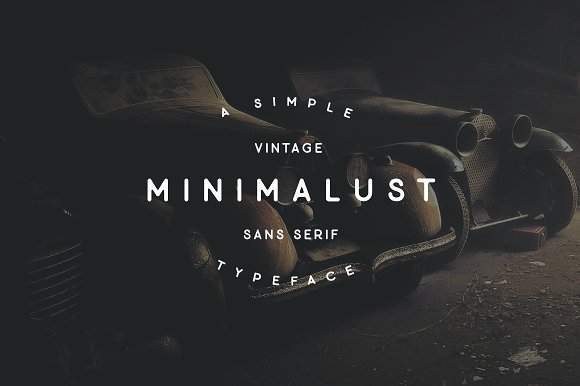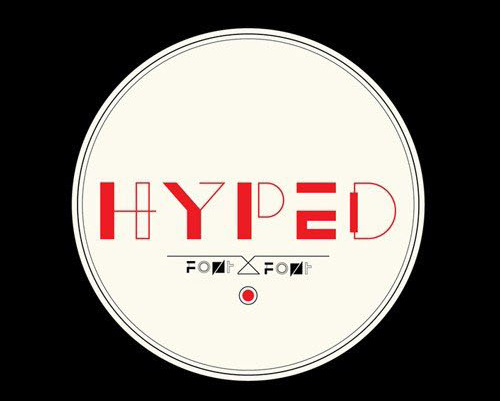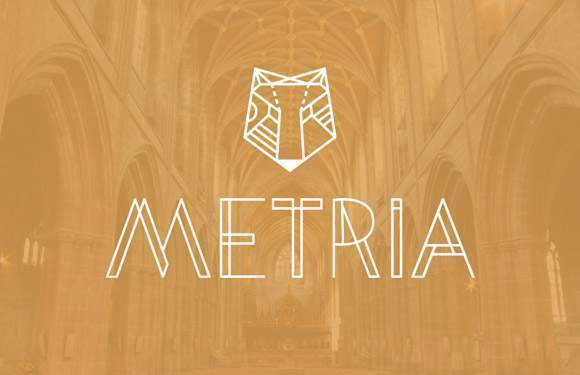
Discover an extensive collection of modern fonts curated specifically for designers who want to elevate their creative projects. Whether you’re working on branding, websites, social media graphics, posters, or print layouts, having the right fonts for designers is essential for achieving a polished and professional look.
Why Modern Fonts Matter
Using modern fonts in your design projects ensures your work feels current, stylish, and impactful. Clean, contemporary typefaces improve readability, highlight key content, and add personality to your visuals. Designers everywhere know that choosing the right free fonts can make the difference between a good design and an outstanding one.
Features of This Free Font Collection
This carefully curated selection of fonts for designers includes:
Sleek sans-serif fonts for minimalist and modern designs
Elegant serif fonts for sophisticated branding
Playful and creative handwritten fonts
Bold display fonts for eye-catching headlines
1. Lombok Font
2. Ailerons Font
Ailerons – это шрифт Adilson Gonzales de Oliveira Junior, вдохновленный моделями самолетов 1940-х годов. Концы каждой буквы наклонены и слегка изогнуты для тонких деталей.
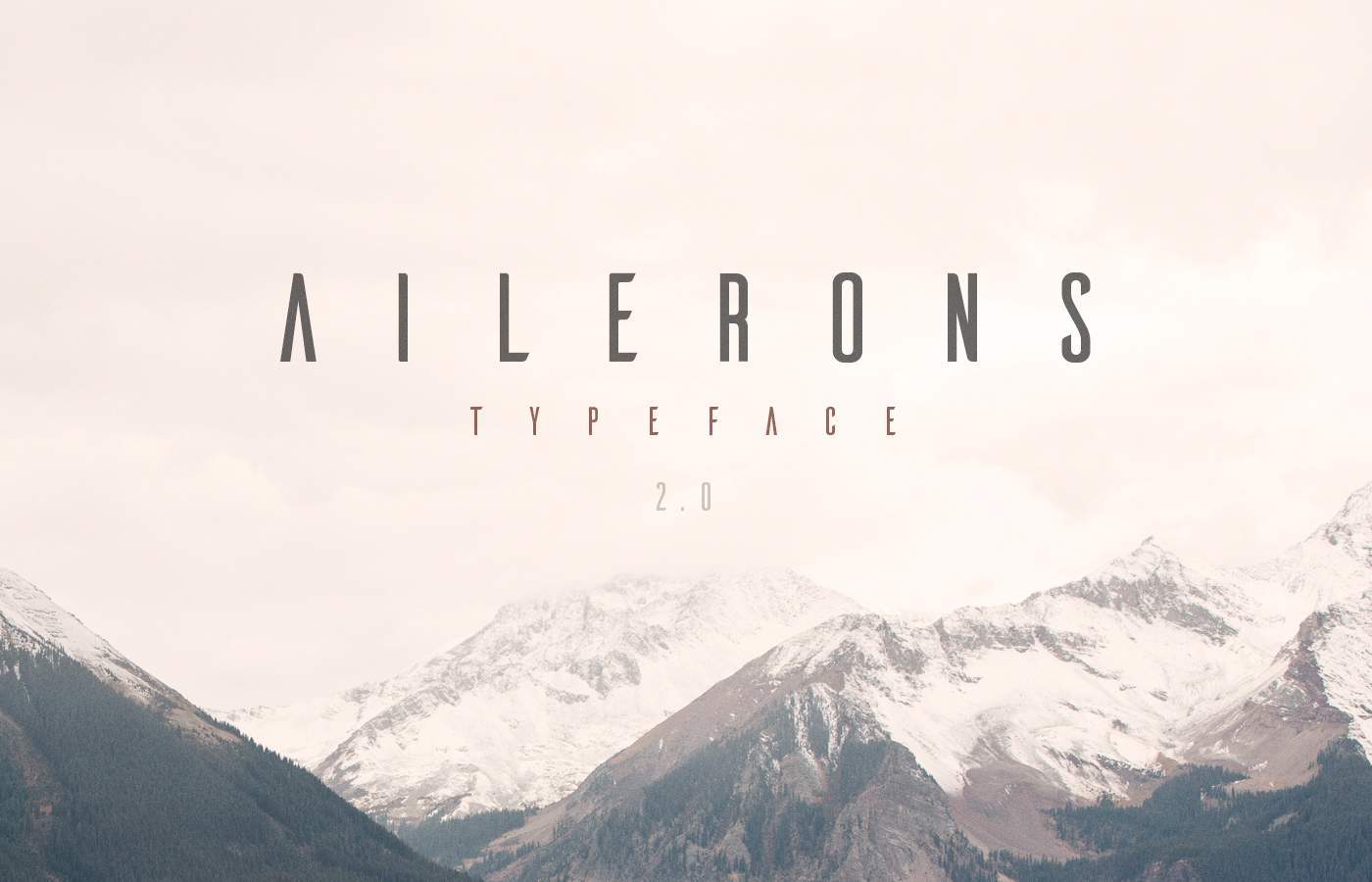
3. One Day Font
One Day – тонкий и заглавный шрифт Nawras Moneer. Его округлые формы и ломаные линии добавят визуальный интерес к любому заголовку.
4. Cooper Hewitt Font
Когда Купер Хьюитт обновил свой музей, он также привлек дизайнера Честера Дженкинса, чтобы создать современный шрифт без засечек, доступный для публичного использования. Теперь это демократический дизайн.
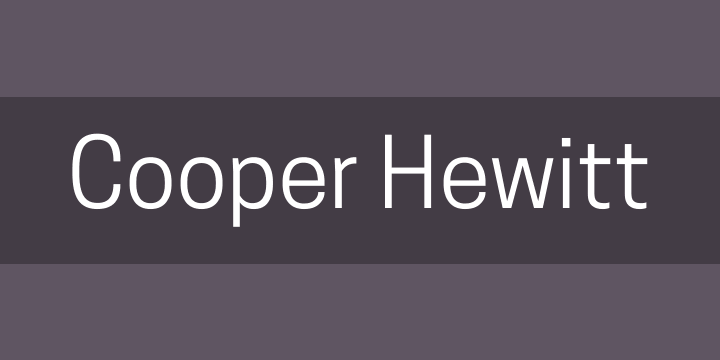
5. Aqua Font
У шрифта Laura Pol Aqua очень прямые линии, которые контрастируют с очень округлыми формами. Сильные углы преобладают над прописными буквами, а гладкие круги – строчными.
6. Kolikö Font
Семейство шрифтов Kolikö by Fontfirma имеет латинские и кириллические символы, в тонких и жирных стилях. Это геометрический шрифт без засечек с чистой структурой для жирных заголовков.
7. Polya Font
Adrien Coquet разработал шрифт Polya, созданный с использованием полигональной сетки с низким полигоном для 3D-моделирования. Результатом является шрифт с жирными формами и легкий внешний вид.
8. Radnika Font
Альфредо Марко Прадиль (Alfredo Marco Pradil) описывает свой шрифт Radnika как «тип рабочей лошадки». Это многофункциональный шрифт, который наводит мосты между сильным и выразительным шрифтом девятнадцатого века и тонким и строгим шрифтом двадцатого века. «Средний» стиль доступен для загрузки бесплатно.
9. Modeka Font
Modeka от Gatis Vilaks – это легкий и элегантный шрифт, который сочетает в себе углы с закругленными деталями. Результатом является набор символов с видимыми соединениями между частями каждого элемента.
10. Higher Font
Создательница шрифта “Higher” – Мариса Пассос. Она предложила этот шрифт для свободного публичного использования. Идеально подходит для заголовков.
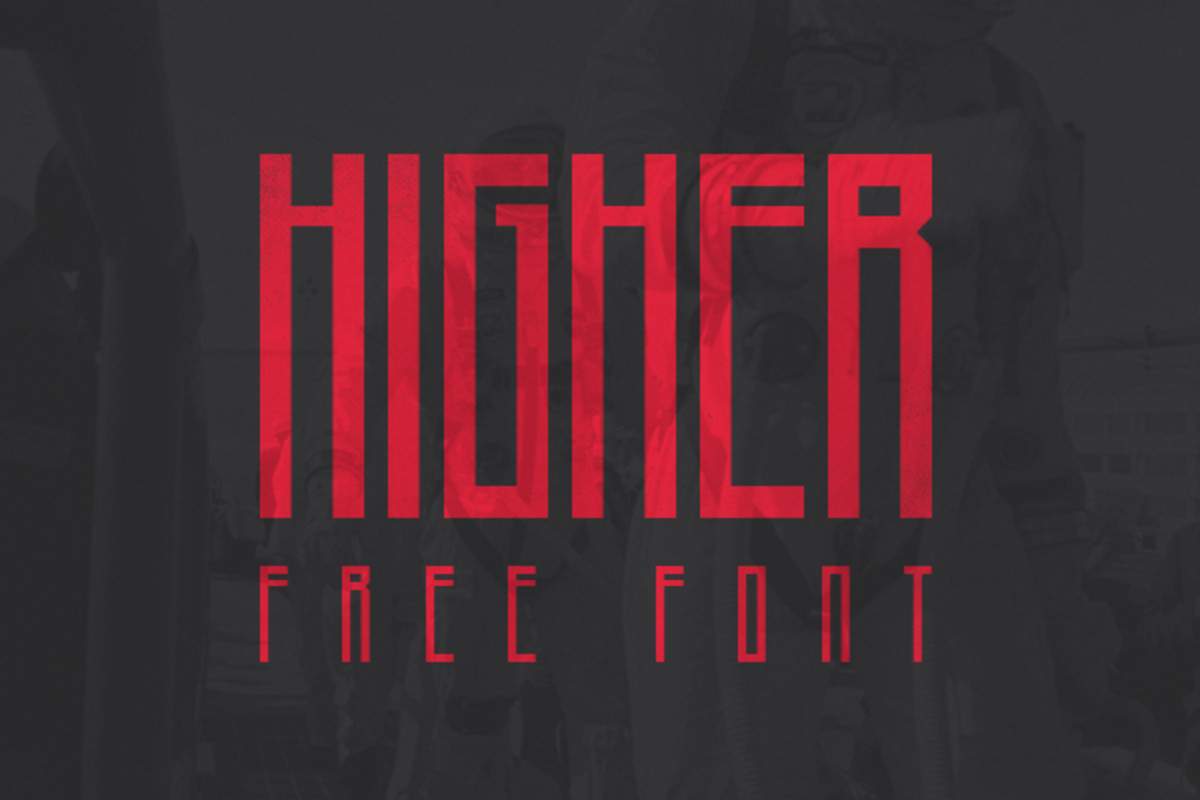
11. Nordic Font
Nordic – экспериментальный шрифт, разработанный Яной Березинер. Он был вдохновлен норвежскими рунами, которые являются буквами, используемыми на различных германских языках до принятия латинского алфавита.
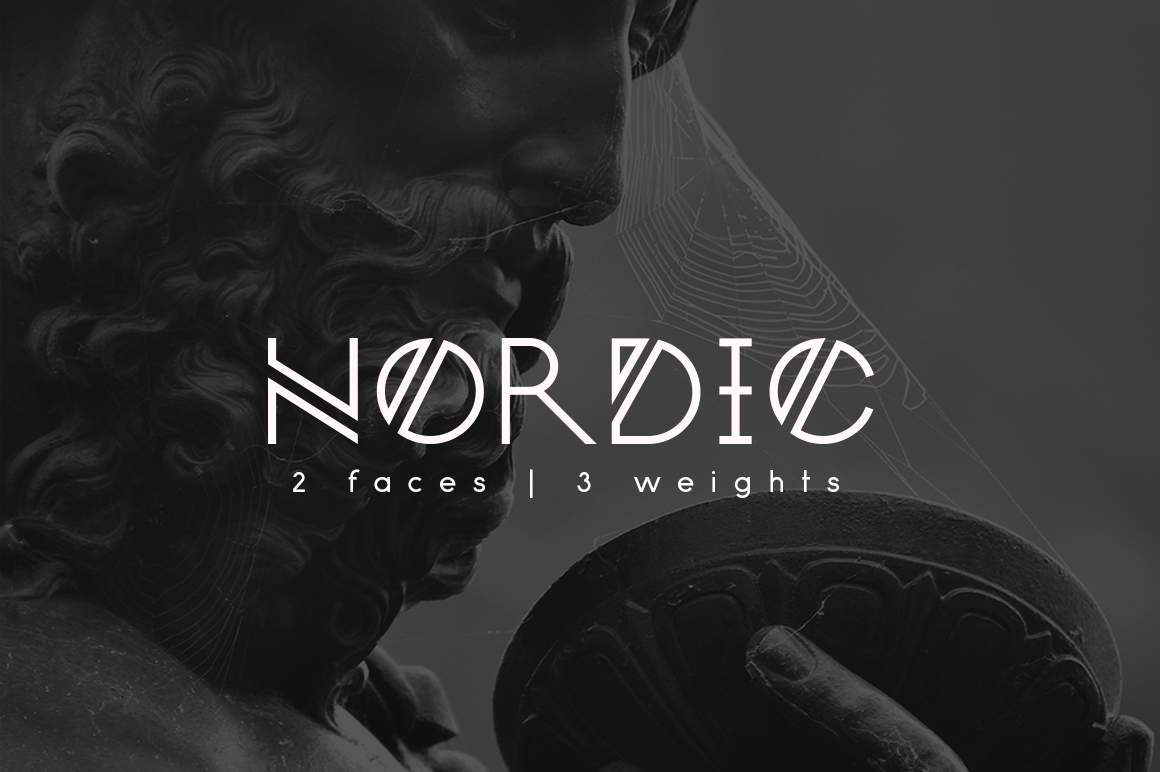
12. Komoda Font
Komoda – тонкий шрифт, разработанный Asia Ang. Он хорошо работает как экранный шрифт для заголовков, выглядит стильно, шикарно и современно – просто заключенный в прямоугольный контур.
13. Kollektif Font
Новый и смелый шрифт – Kollektif созданный в качестве альтернативы низкоконтрастным шрифтам двадцать первого века.
14. Achi Font
Achi является первым экспериментальным шрифтом Shibu PG. Это современно и стильно, а двойные стебли и штрихи придают детали ар-деко.
15. Parley Font
У шрифта “Parley” есть интересные диагональные линии, которые разрезают каждую букву и цифру; Некоторые из них являются частью текста, а другие являются дополнительными деталями.
16. Aroma Font
Лаура Поль также создательница шрифта Aroma. Доступный жирным шрифтом и обычным. Шрифт современный с изогнутыми и угловыми углами, которые немного ретро и немного каллиграфичны.
17. Boxing Font
Шрифт Tano Veron’s Boxing обеспечивает стиль из-за его тонких, вытянутых и уплотненных линий. При создании шрифта, автор был вдохновлен ретро-боксерскими плакатами.
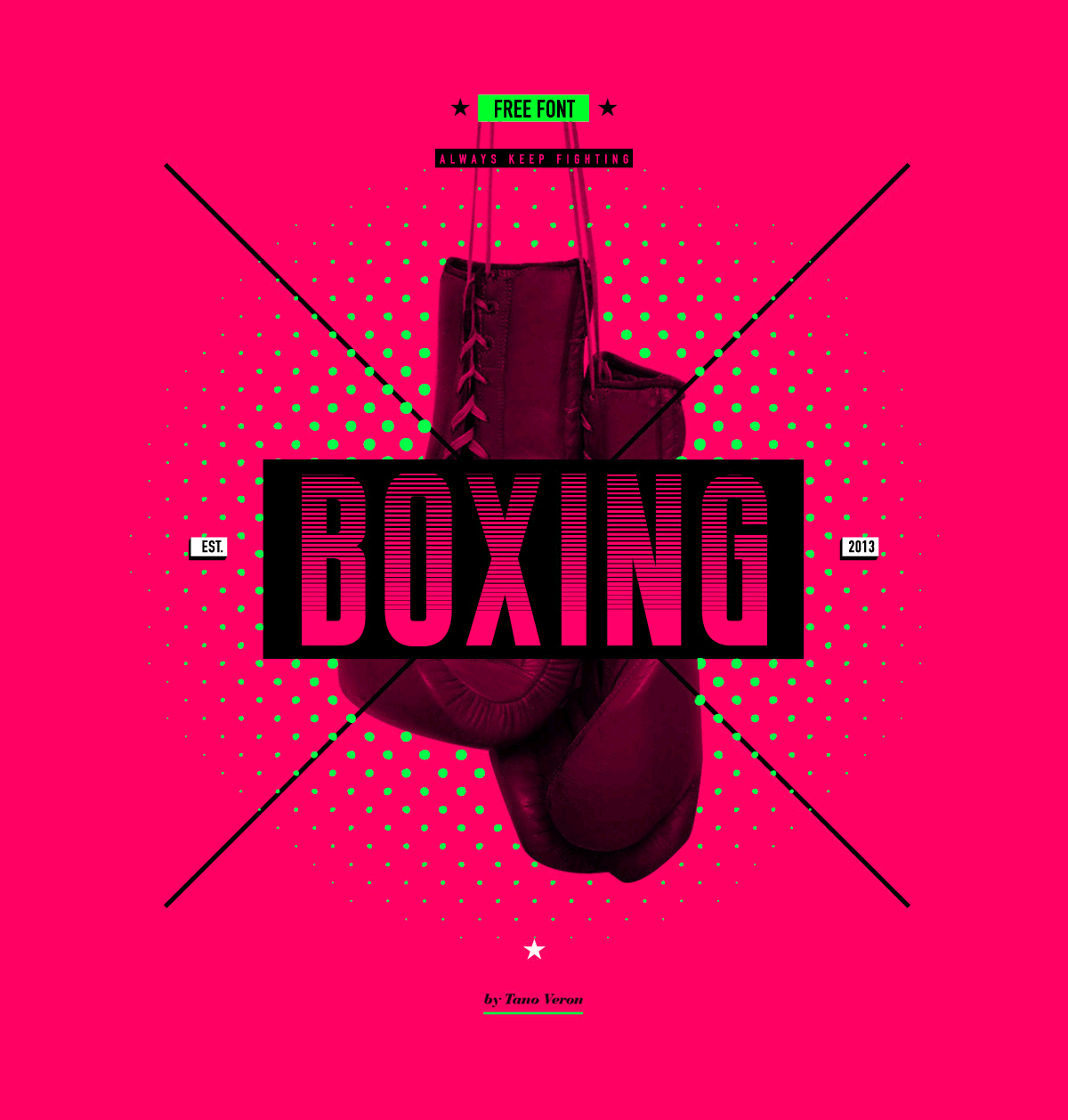
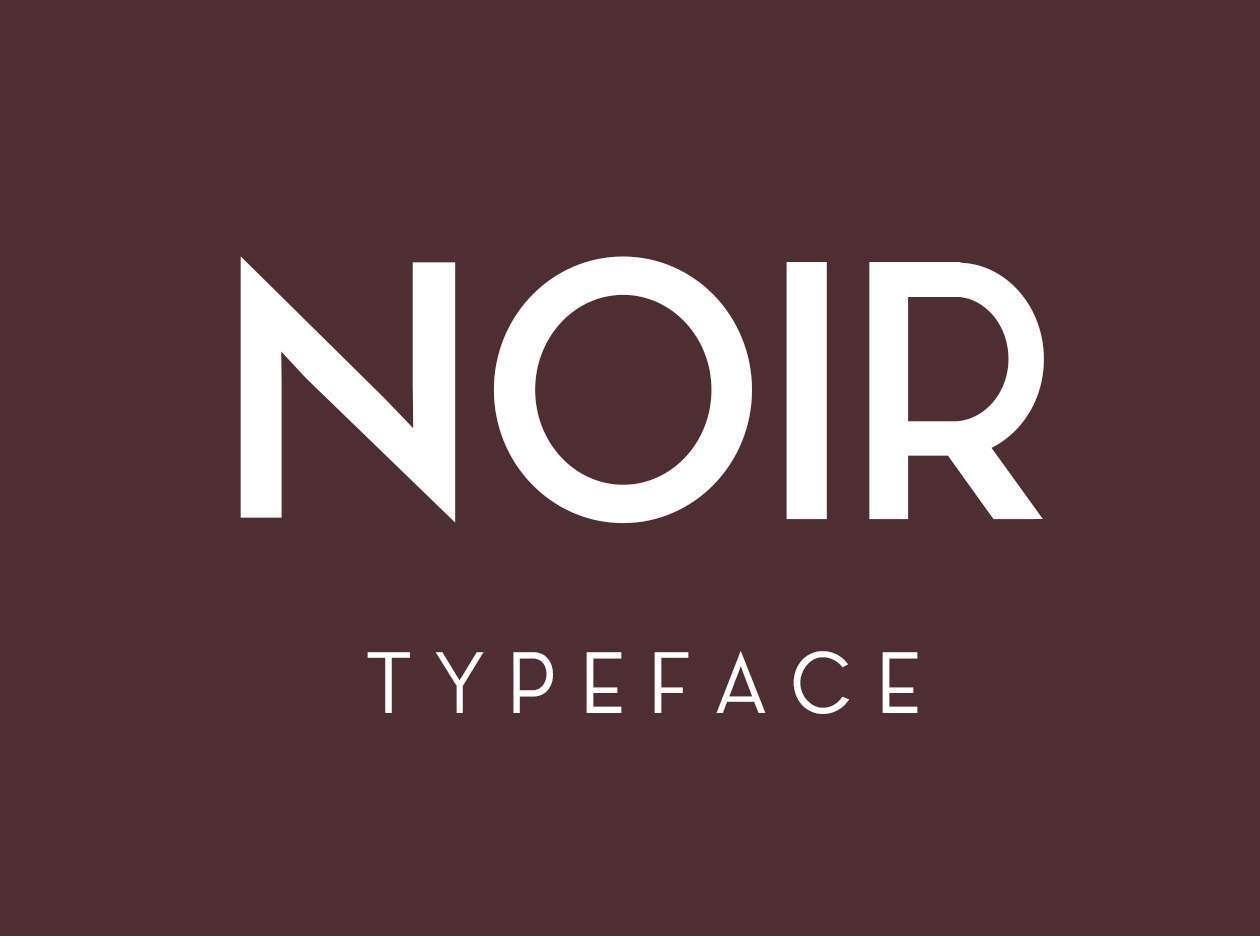
49. Glober Font
Шрифт Fabric’s Glober вдохновлен классическими гротескными шрифтами. У него есть свой собственный уникальный стиль, выраженный через смягченные геометрические формы, которые являются легкими и изящными. Плюс проверьте, что строчная буква ‘g’ – это часть дизайна.
50. Canter Font
Разработанный Кристофером Дж. Ли, Canter – это всеохватывающий, уплотненный шрифт, который хорошо подходит для отображения титров, заголовков и плакатов.